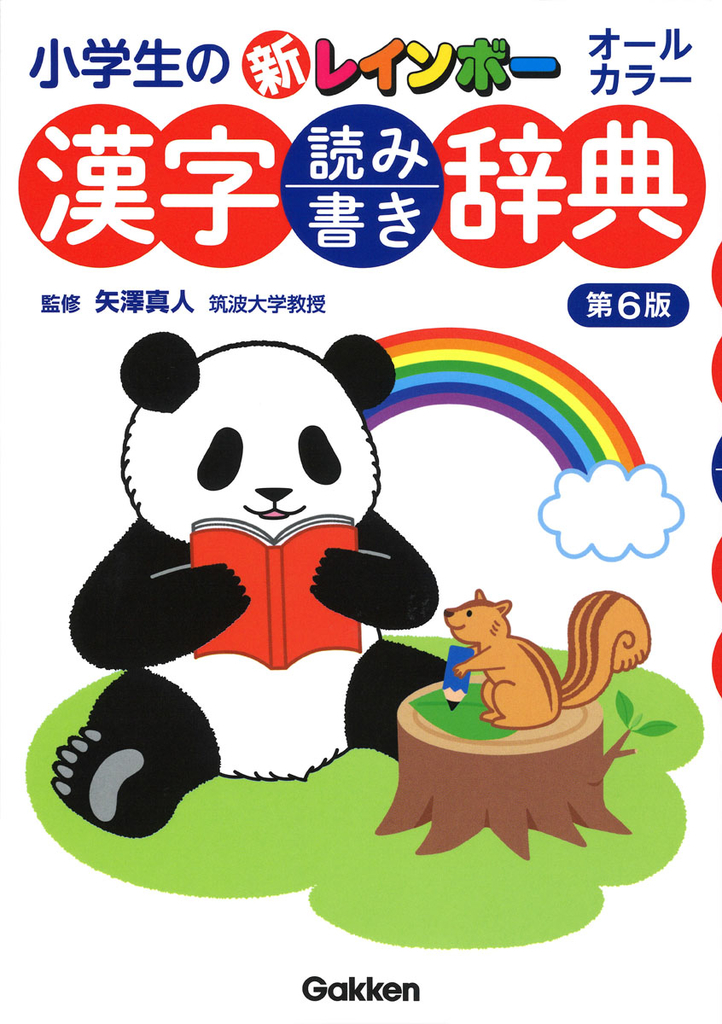
小学生の新レインボー 漢字読み書き辞典 第6版(オールカラー)
学研ホールディングスのグループ会社である学研プラスは、2018年12月7日(金)に「小学生の新レインボー 漢字読み書き辞典 第6版(オールカラー)」を発売した。
「小学生の新レインボー 漢字読み書き辞典 第6版(オールカラー)」は、新しい情報に対応した漢字辞典となる。
2020年度から小学校では、新学習指導要領に対応する新教科書で授業が行われる。国語の授業では、学習する漢字が増えて、漢字を学習する学年が変わる。
小学4年生の国語科では、都道府県名で使われる「茨・媛・岡・潟・岐・熊・香・佐・埼・崎・滋・鹿・縄・井・沖・栃・奈・梨・阪・阜」の20字が追加。
また、小学校では各学年で習う漢字が決まっており、新学習指導要領では、1、2、3年生はこれまでと変わらないが、4年生に都道府県の漢字を集めるなど、4、5、6年生で入れ替えが行われる。
※2018年度から2019年度までは移行期間なので、学校によっては新学習指導要領で指導される。
2020年度には、2年生は4年生に、3年生は5年生に、4年生は6年生になります。1年生も、2021年に4年生になれば、新しい学年配当で漢字を習うことになる。
機会を逃してしまうと、ついつい古い情報の辞典を使いっぱなしになってしまうため、新しい情報が入った漢字辞典で学習してみるのも良さそうだ。
漢字を学年別にまとめて示しており、学年ごとの漢字を順番に学習できる親切なつくりになっている。それぞれの漢字には「使い方」を複数掲載していて、その漢字を文章の中で実際にどのように使えばよいか一目瞭然。各漢字には、日付の記入欄を設けている。漢字学習の履歴と達成度合いが一目でわかる。そうすることで達成感が得られて、学習意欲につながる。
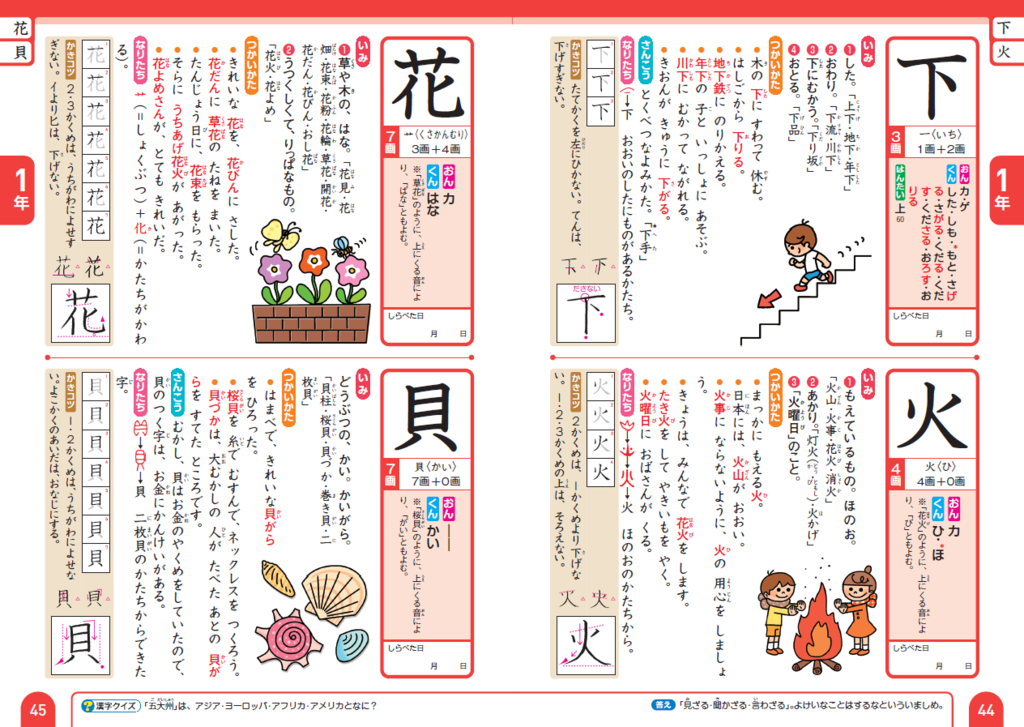
▲小学1年生の本文。1年生と2年生は1ページに2漢字。漢字1字につき、イラストが1つ。大きく読みやすい。
▲小学4年生の本文。3年生から6年生までは1ページに3漢字。ここでは、「媛」と「岡」が追加の漢字。
漢字を覚えるのが苦手。漢字がじょうずに書けなくて困っている。この辞典はそんな悩みにも対応。
漢字を覚えるには正しい筆順を覚えることが大切だと言われている。この辞典では、筆順を全コマで表示しており、書く順番を迷うことなく練習ができて、漢字が正しく書けるようになる。
また、「書きコツ」コーナーを各漢字に掲載。字形の整え方などが赤い字で示されているから、漢字が美しく書けるようになる。さらに、悪字例も示しており、どうしてバランスが悪くなるかも説明。自分の書いた字と向き合うことで、より美しく書く助けになる。
索引も充実しており、漢字辞典の引き方学習もできる。漢字辞典の基本的な3つの索引、音訓索引・総画索引・部首索引もついており、引き方学習ができる。小学4年生で習う「漢字辞典・漢和辞典の引き方」にスムーズに取り組むことができて、一石二鳥になっている。